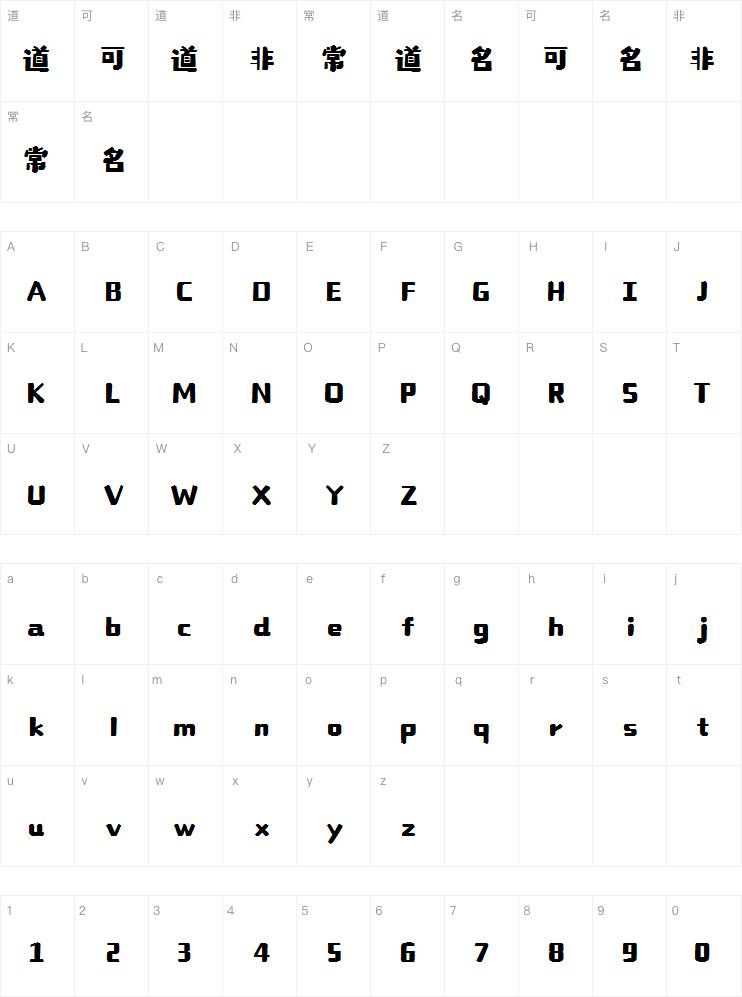
山海便利贴,是一款全新的字体,包含汉字9169个,符号200+个。该字体是一款卡通风字体,该字体字形灵动多变,童趣可爱,结构多变灵动,字形活泼清新,造型生动有趣,具有灵活的适用性,天真俏皮又不失时尚感。该字体字形大小不一,灵动跳脱,字形重心一致,各种几何图形组合成不同笔画,笔触方中带圆,笔画布局在多变的同时有保持整体均衡匀称。灵动笔画贯穿笔画始终,内涵丰富,弧度柔和,撇笔平缓舒展,尽显俏皮灵动。